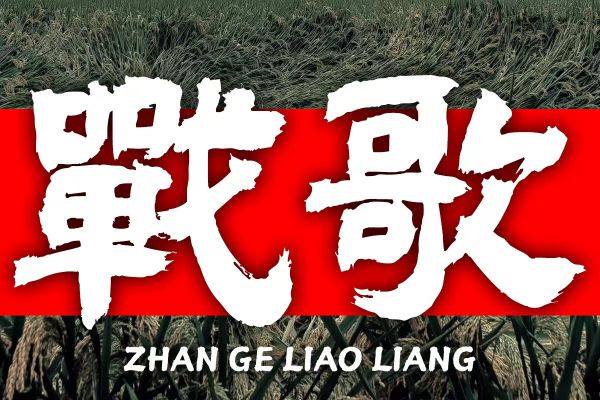
汉仪黄科壮隶 W
汉仪黄科壮隶 W是汉仪字库推出的粗体手写体字体,以中国风为核心,融合古典隶书底蕴与现代设计审美,兼具力量感与艺术表现力,适配简繁中文多场景应用。 汉仪黄科壮隶 W在字形结构上独具特色:整体方正规整,重心居中沉稳,中宫宽博舒展,既延续隶书“蚕头燕尾”的波磔挑势传统,又以斜切笔型与方头笔画设计强化刚劲质感。笔画粗细均匀却暗藏节奏,断开的连接方式让字间留有呼吸感,墨色飞白的自然晕染更添手写艺术的灵动,呈现“遒劲刚健、古意盎然”的视觉效果。 作为支持单独授权与品牌定制的专业字体,汉仪黄科壮隶 W适用于传统文化艺术宣传、民俗节庆设计、美食餐饮包装等场景,在广告海报、书籍封面、影视字幕中既能凸显古典韵味,又能以粗重笔力传递品牌力量,是平衡传统美学与现代传播的手写体优选。